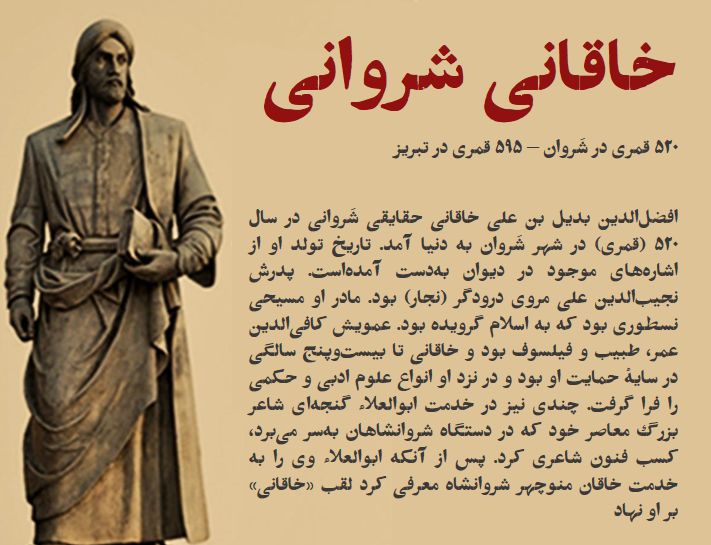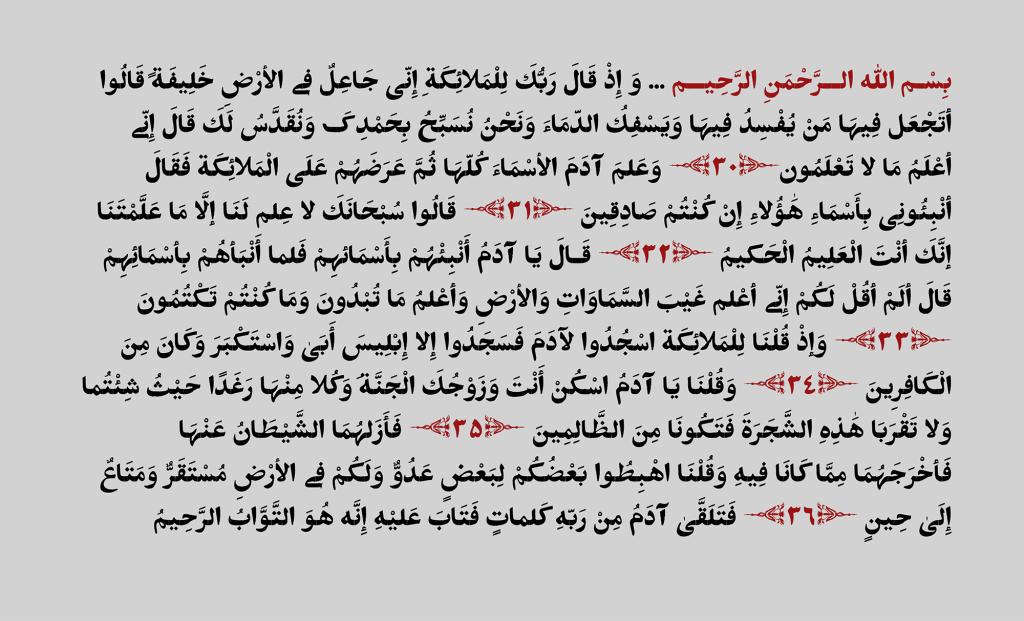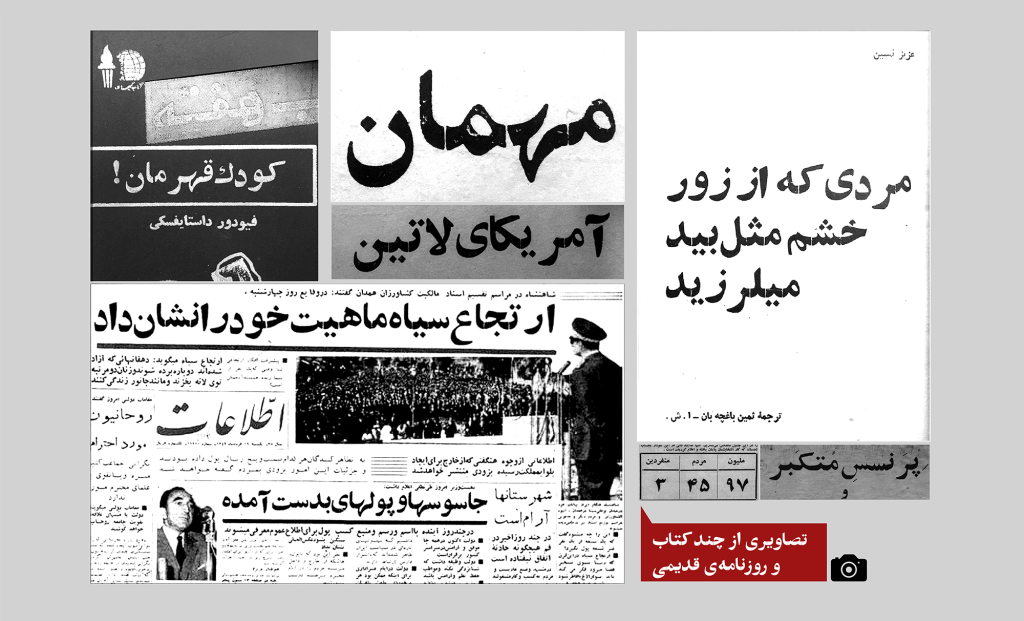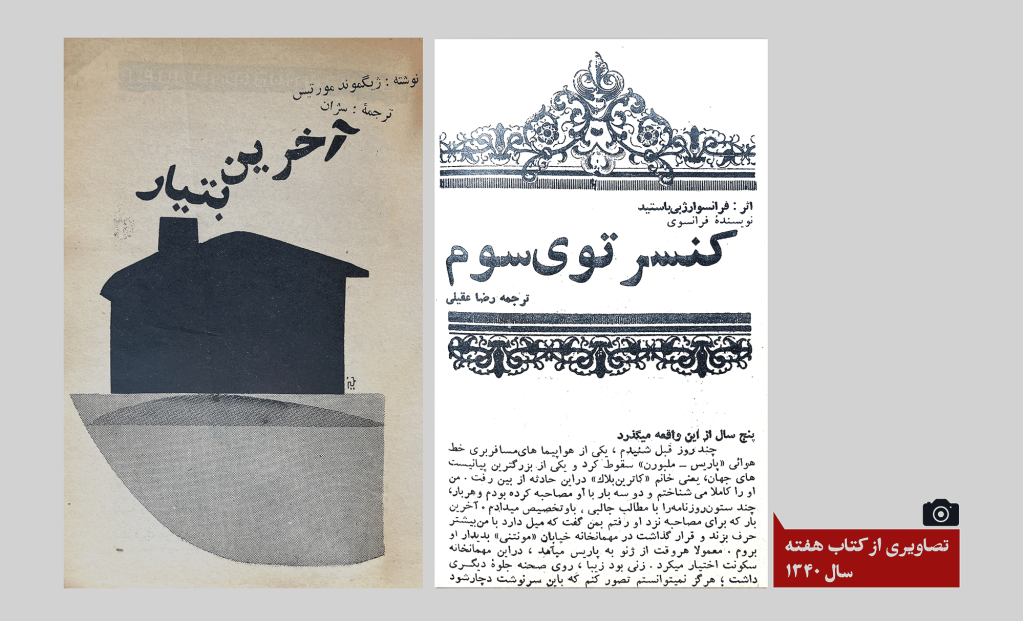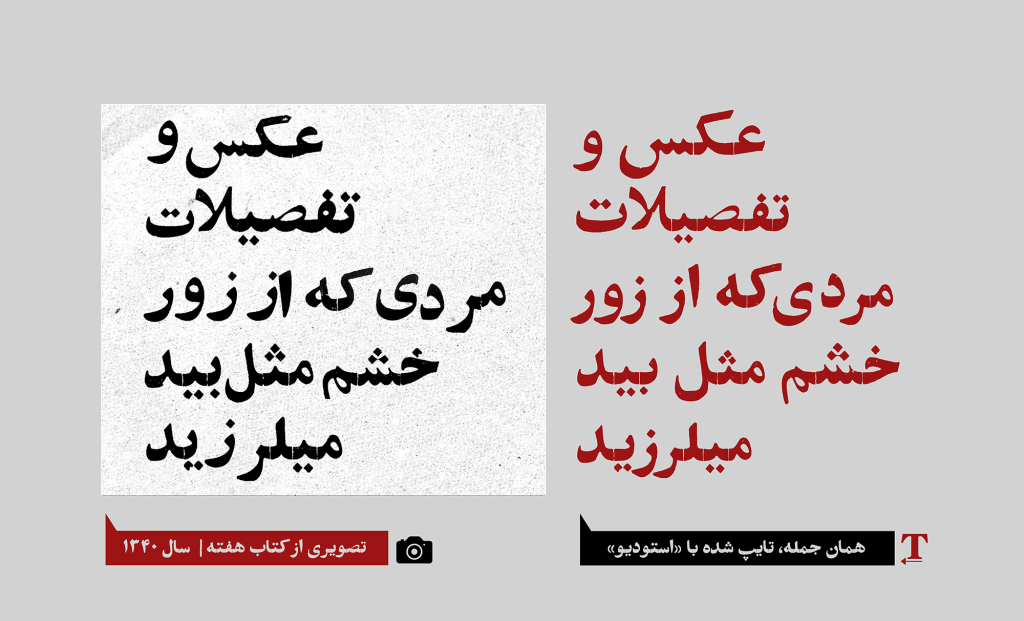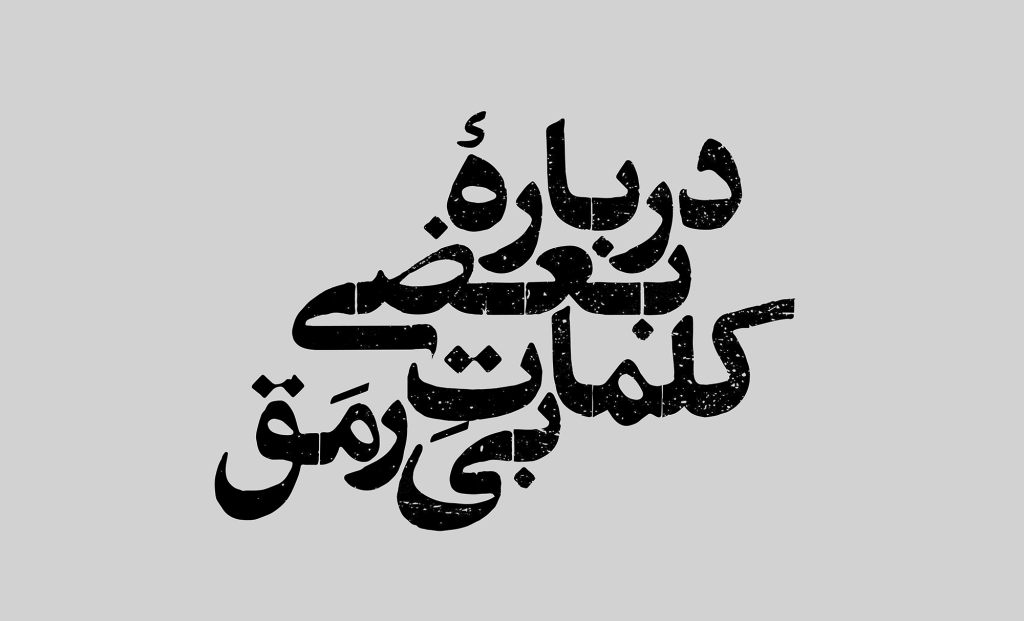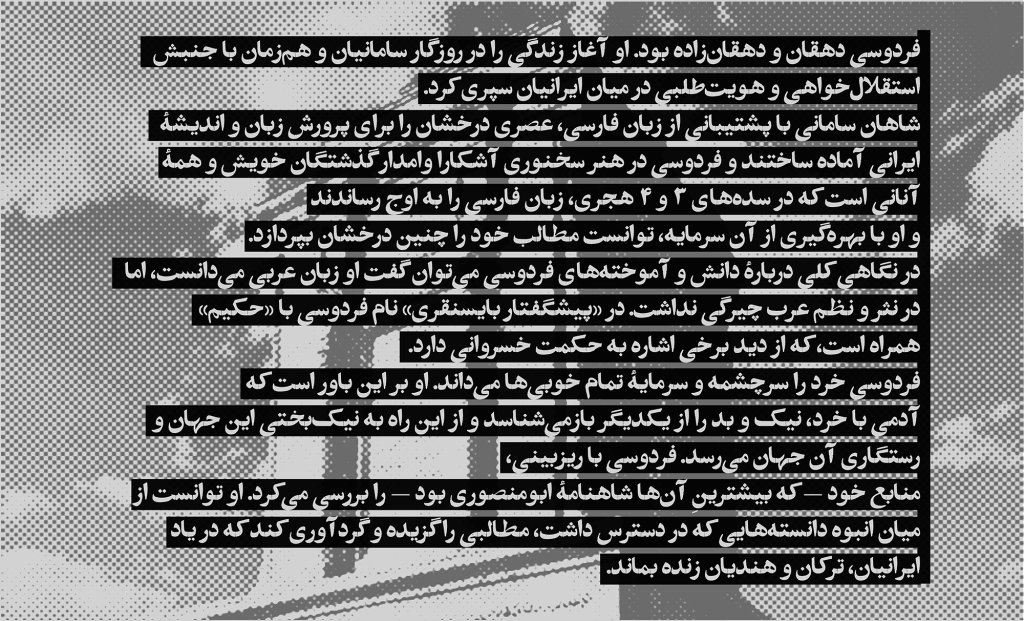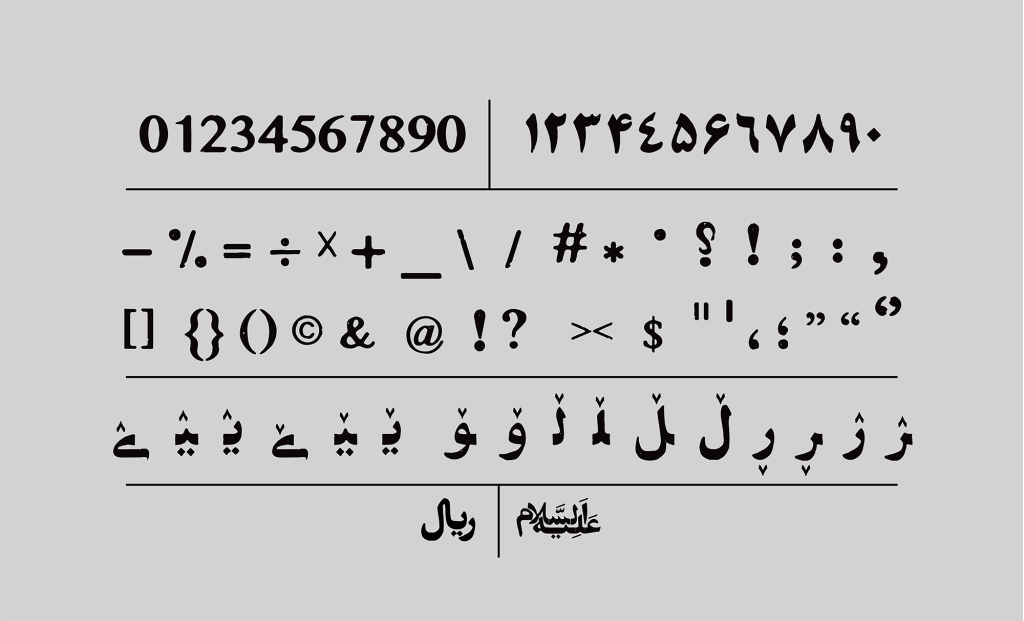
فونت استودیو – مسافر قدیمی
فونت استودیو مسافری از دیار و روزگاران کهن بوده که سوار بر علم و تکنولوژی قرن معاصر به دنیای امروز ما پا نهاده است.
اگر به دنبال قلمی با حس و حال و اتمسفر قدیمی هستید گویی که از سالیان گذشته پا به عرصه حال حاضر نهاده است استودیو همان گمشده شماست. طراحان گرافیک، طراحان فضای مجازی و وبسایت، ناشران، مطبوعات، طراحان صحنه، هنرمندان و همهی آنها که به نوعی با تایپفیسهای فارسی سروکار دارند، همواره به دنبال حروفی با حال وهوای قدیمی، برای ساخت فضاهای نوستالژیک مواجه هستند.
به جرات می توان گفت قدمت و سابقه استودیو به حدودا ۷۰ سال پیش دوره چاپ به شیوهی «سُربی» برمی گردد. که
با خروج و کم رنگ شدن حروف سُربی از گردونۀ تولید، این فونت نیز رفتهرفته به محاق فراموشی رفت. از این حیث جهت معرفی قلمی فوق العاده زیبایی که هم شکل و هم خانواده استودیو می باشد می توان هاکذا اشاره نمود . توصیه ما به شما دوست داران به این سبک از قلم های فارسی مشاهده فونت هاکذا می باشد.
استودیو تایپ فیسی با اصالت
حفظ اسکلت و ریخت شاکله اصلی این قلم قدیمی مهم ترین اصل در طی مراحل بازسازی آن بوده است. مشخص است که شکل حروف و اتصالات تناسب دقیقی با هم ندارند، بعـضی به صورت صحیح بر روی خط کرسی قرار ندارند و تناسب و اندازهی حروفِ همسان لزوماً شبیه به یکدیگر نیست. در محیط و سطح حروف بافتها و خوردگیهایی مشاهده میشود.
همچنین در نسخه نهایی، کاراکترهای اول، وسط، آخر و تنهای حروف، هر کدام شکل و بافتِ مختص به خود را دارند و اینطور نیست که مثلاً خانواده حروف «س» و «ش» تنها با اضافه کردن چند نقطه ساخته شده باشند.
این تایپ فیس سال ۱۳۹۶ در استودیو دفتر و تحت نظر و کارشناسی مجید کاشانی بازسازی، اصلاح و اجرا و دفرماسیون آن انجام گردید. تعداد زیادی روزنامه، کتاب، مجله و آگهیهای قدیمی، منابعی بودند که برای استخراج حروف و ترکیبات مورد استفاده قرار گرفتند.
استودیو دارای شخصیتی اصل و با اصالت است که یادگاری از روزگاران گذشته بوده که اکنون به زمان حال آمده تا برای زنده کردن حس و حال فضای قدیمی و نوستالژیک رسالت خود را انجام دهد.